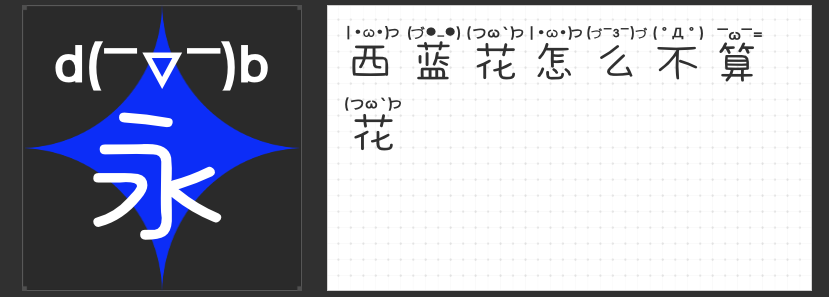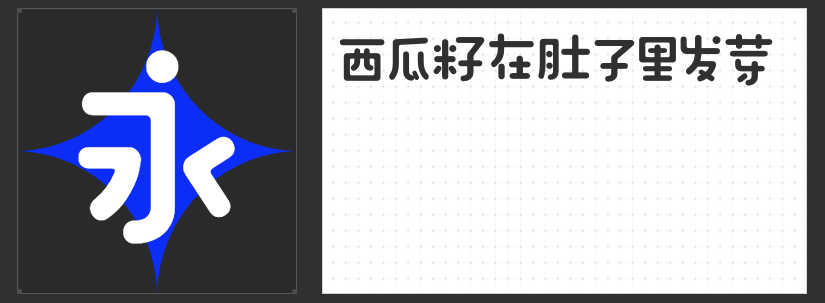
六一儿童节创意设计字体推荐:四款童趣字库字体点亮童真
六一儿童节不仅是孩子们的狂欢,更是设计师展现创意的舞台。如何通过字体传递童真、活力与独特个性?今天精选的四款商业授权字库字体,以风格化的笔触与灵动的结构,为儿童节设计注入无限想象力。
一、励字造桃气圆 准粗
这款字体以手写感为基调,将圆体字型的“上松下紧”结构演绎得松弛而灵动。重心略低的设计赋予文字一种俏皮的“小步伐”感,笔画圆润饱满却充满变化:折笔处内外圆角交替,部分笔画被圆形元素替代,形成视觉的跳跃感;笔画间的“断开”处理更让文字如音符般轻盈,仿佛在纸面跳跃。它既适合儿童品牌LOGO的童趣表达,也能作为海报标题,搭配手绘插画营造治愈氛围。
二、字恋狂嗨玩简
粗壮的笔画、方正的字形,这款字体如同积木拼接般充满童趣。重心靠下的设计让文字自带“憨厚”气质,笔画转折处保留手工感的钝角,仿佛孩子用蜡笔一笔一划勾勒而成。它的“笨拙感”正是魅力所在——无论是儿童零食包装上的标题字,还是幼儿园活动海报的视觉焦点,都能以反差萌打破常规,传递纯粹的快乐。
三、字恋狂特别黑简
横粗竖细的强烈对比,让这款字体如孩童涂鸦般充满张力。笔画粗细的戏剧性变化打破常规结构,折笔处保留手写的不规则感,个性张扬却毫无刻意感。它适合作为儿童节主题活动的核心视觉,比如户外游乐场的巨型标语,或是电子海报中抓人眼球的标题,用野性的生命力点燃节日氛围。
四、字圈也字可爱颜文字体
横斜竖直、左低右高的结构赋予这款字体一种“小叛逆”的姿态:折笔处时而钝角如笑脸,时而直角如棱角,圆润与尖锐并存,仿佛孩子用彩色蜡笔在纸上自由挥洒。它的笔画坚定有力,走向自信,如同孩童不受拘束的内心世界。无论是儿童社交媒体的表情包设计,还是文具产品的包装文案,都能以独特的“自我表达”引发共鸣。
四款字体风格迥异却都充满童真,在六一儿童节设计中,它们能成为品牌与孩子对话的桥梁,用字体语言诉说童年的无限可能。
让这些充满童趣的字体,为节日增添一抹别样的色彩吧!